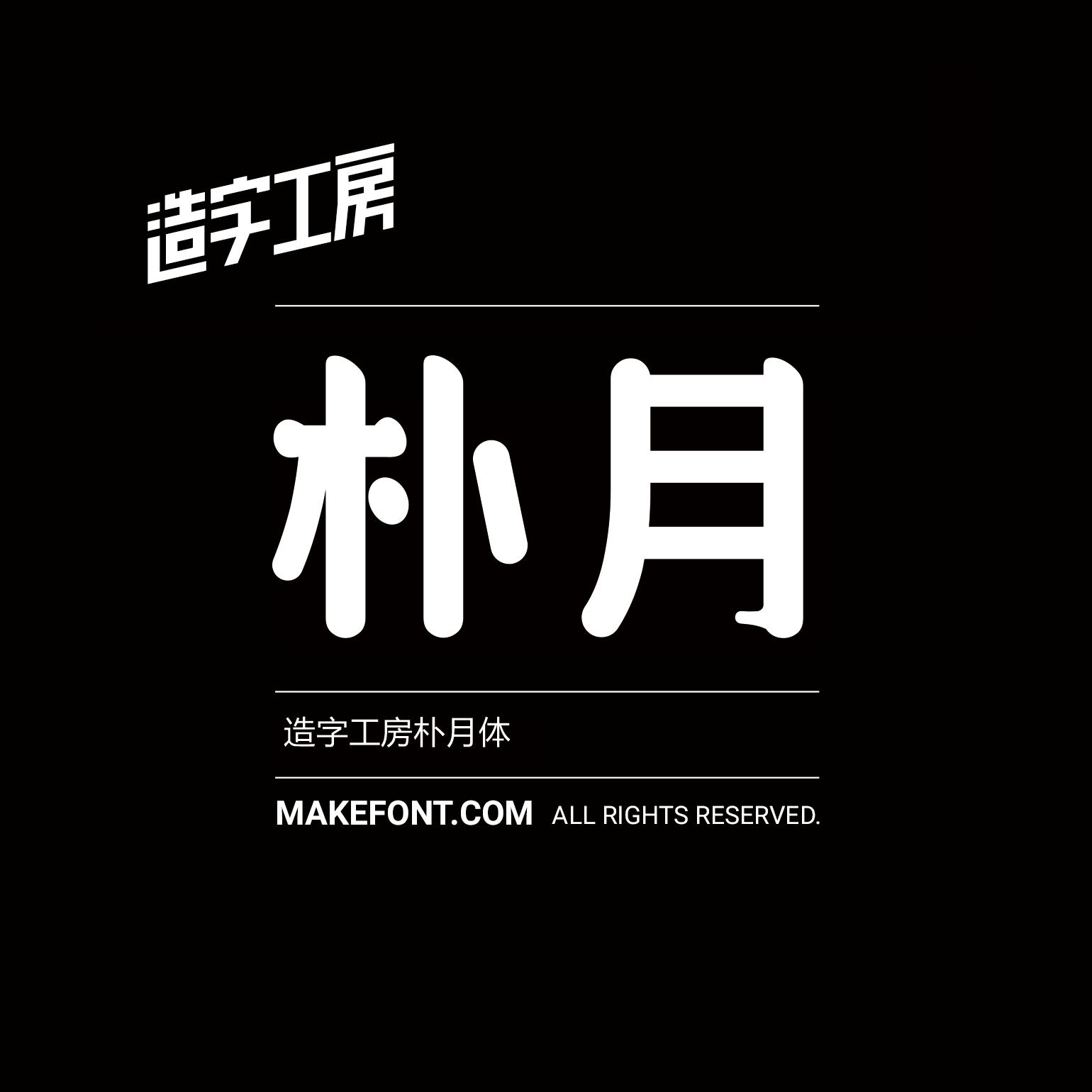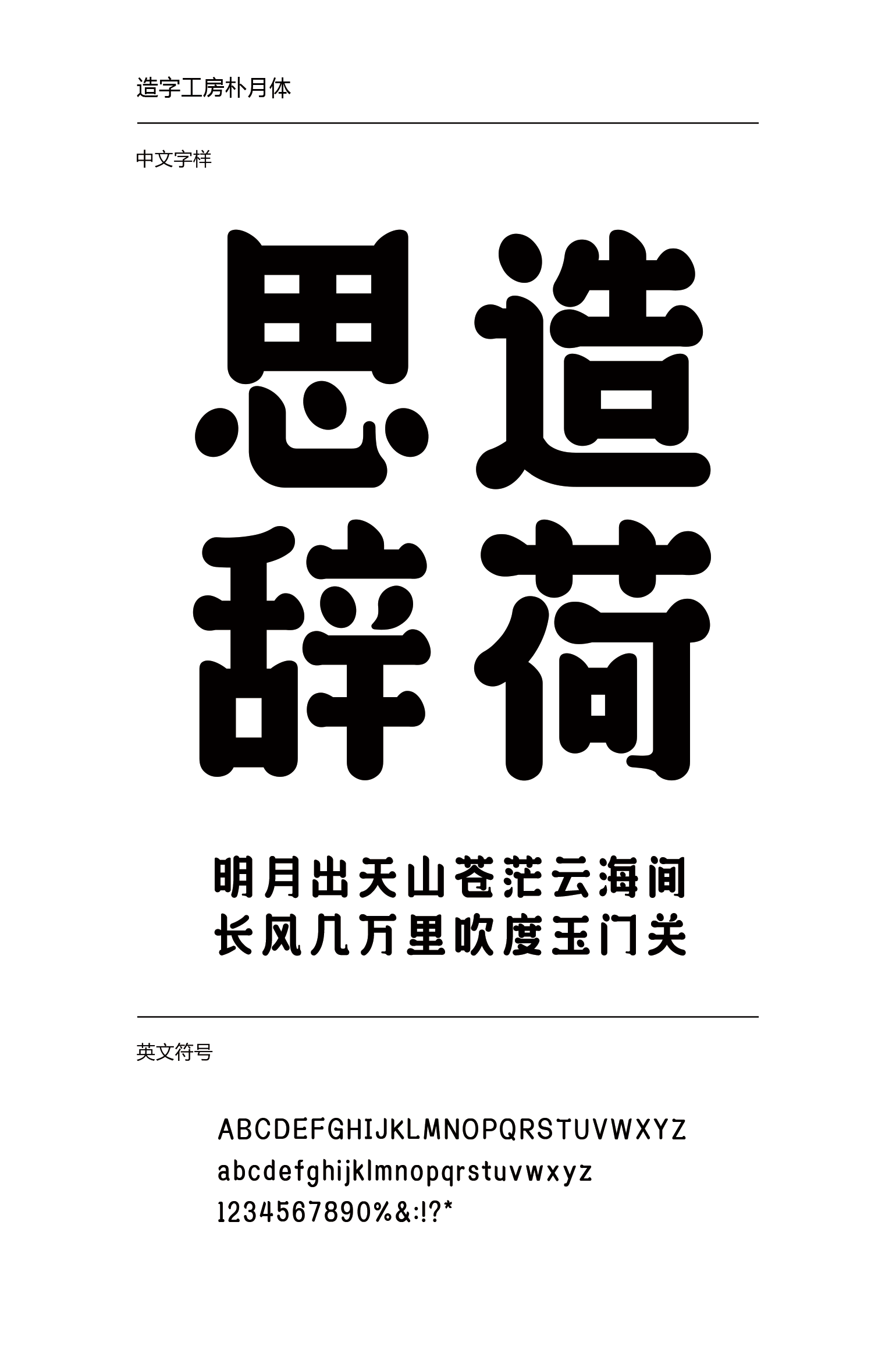
造字工房朴月体
造字工房朴月体设计说明
造字工房朴月体字体端秀清新,笔画方圆兼备,曲线舒展,横画首尾呼应,温润秀美,整体风格不燥不润、张弛有度,有极强的视觉表现力。适用于大标题及个性品牌设计推广等环境。本字体为简体字库,采用OpenType/CID格式,Adobe-GB1-5编码。基于中华人民共和国GB2312-80字符集标准,另按需添加101个汉字。共收容字数6864CJK汉字,ASCII常用字符100个。